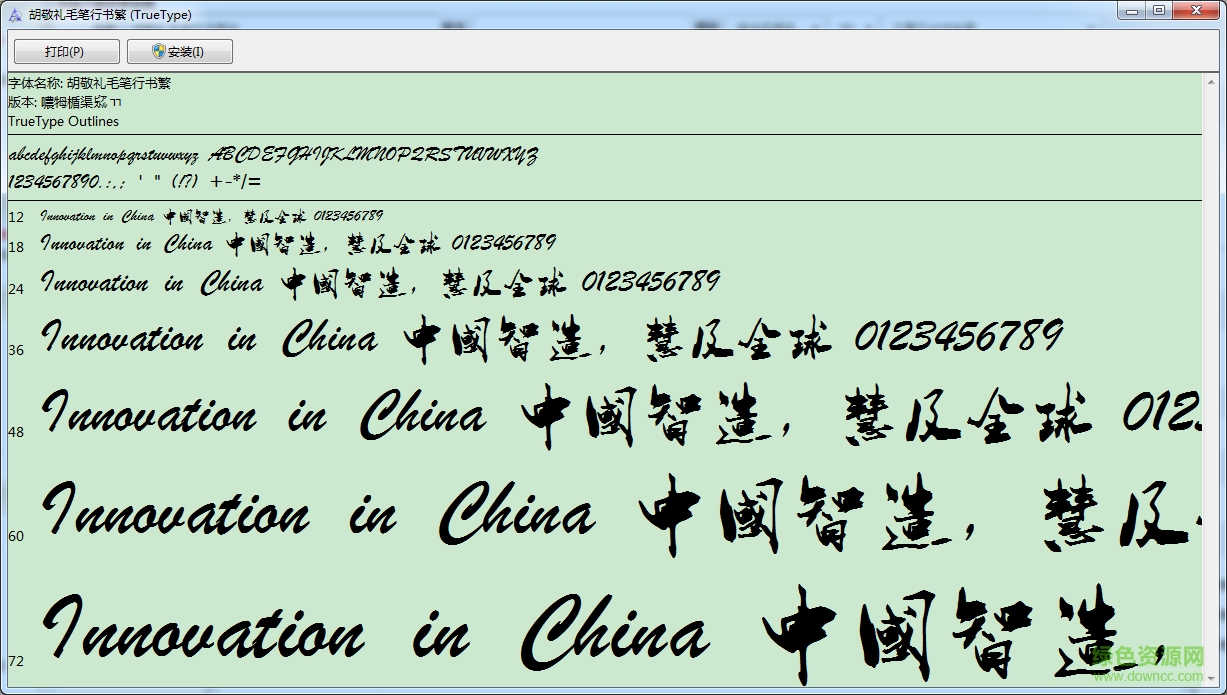
軟件介紹 軟件標(biāo)簽: 毛筆行書 毛筆字體 hujingli-fan字體是一款繁體的毛筆書法字體,雄渾大氣富有張力,細(xì)節(jié)處理精致,整體結(jié)構(gòu)非常和諧,給人一種隨意靈動的感覺,既蘊含濃厚的書法意味又不失實用性,喜歡的朋友快來下載吧!書法題字分類1、廣告宣傳題字;2、藝術(shù)收藏題字。3、禮儀紀(jì)念題字;4、人文景觀題字;5、文化品牌題字6、影視書刊題字;hujingli-fan字體安裝方法一:控制面板/字體/文件/安裝新字體;二:直接將字體復(fù)制到C:\WINDOWS\Fonts。三:針對win7系統(tǒng),用戶只需選中字體右鍵安裝即可。 軟件截圖 上一張下一張(1 / 1) 安裝詳細(xì)截圖 猜你喜歡 行書字體 行書字體 行書字體包括了鋼筆字行書字體大全、硬筆行書字體等,是一種介于楷書和草書之間的字體。為什么這樣說?因為行書字體既有草書的流暢感,又有楷書的端正感,可以說,行書結(jié)合了草書和楷書的特點,形成了獨特好看的行書字體。喜歡的朋友,趕快下載體驗吧! 查看更多>> 繁體行書字體 9.76M/中文/4.0/免費版下載 winman tun10011字體 17.57M/中文/6.6/下載 南構(gòu)嘉飛行書字體 10.00M/中文/6.6/下載 c g流麗行書體繁/簡 4.39M/中文/5.0/下載 北方行書簡體 2.63M/中文/7.2/下載 qxyingbixing 1.26M/中文/8.0/下載 其他版本下載 標(biāo)題 大小 更新日期 下載 下載地址 電腦版 hujingli-fan 點擊報錯 軟件無法下載或下載后無法使用,請點擊報錯,謝謝! 關(guān)閉報錯反饋 請描述您所遇到的錯誤,我們將盡快予以修正,謝謝! *必填項,請輸入內(nèi)容 本類最新 datm9 datx2 datk8 dath9 datk6 書法家特圓體字體 相關(guān)文章 Linux 防火墻配置基礎(chǔ)篇 新手如何遠(yuǎn)程管理windows2003服務(wù)器 Linux下FTP的配置與應(yīng)用 LINUX下MYSQL完全安裝使用指南 linux網(wǎng)站建立步驟 Exchange 2000 Server的常見問題 用戶評論 熱門評論 最新評論 發(fā)表評論 查看所有評論(0) 昵稱: 請不要評論無意義或臟話,我們所有評論會有人工審核. 字?jǐn)?shù): 0/500 (您的評論需要經(jīng)過審核才能顯示)